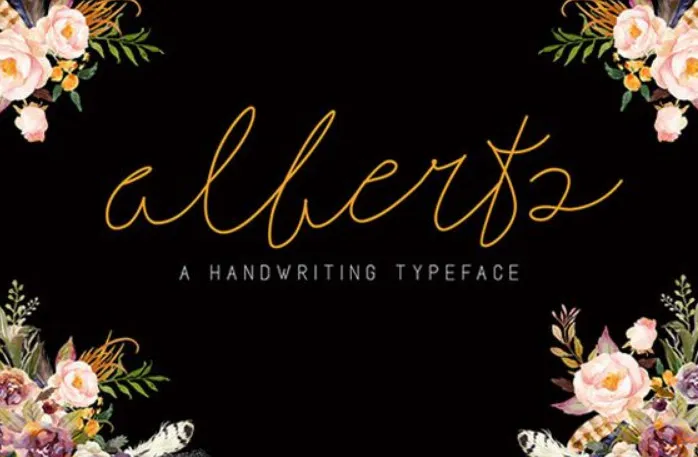
Alberts Script Font – Download Grátis
A AlbertsScript Font é uma deliciosa escolha para quem busca dar vida a designs gráficos modernos com sensibilidade e personalidade. Esta tipografia é um estilo original que transmite uma atmosfera de escrita por conta própria, perfeitamente adequada aos desafios da criação contemporânea. Com seu fluído e elegante traçado, esta fonte é ideal para grandes texturas, garantindo que cada página se torne uma verdadeira expressão única. É especialmente atraente para projetos como estaçãores de casamento, convites e citações, tornando qualquer conteúdo mais agradável e atraente. Seja em um design formal ou informal, a AlbertsScript Font traz vida ao seu trabalho, elevando-o acima do básico para algo especial e memorável.